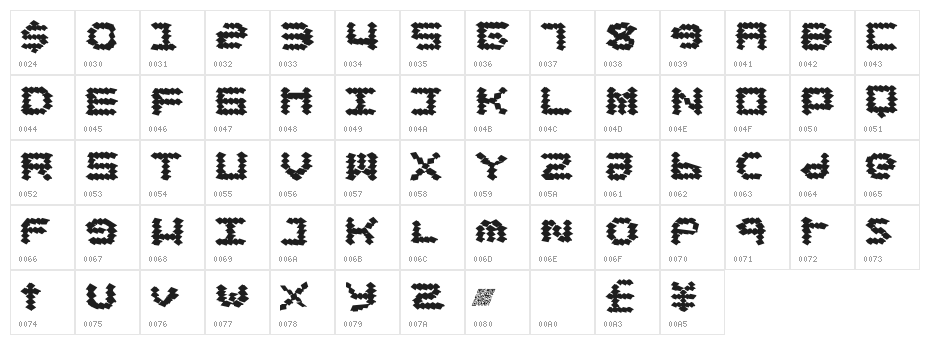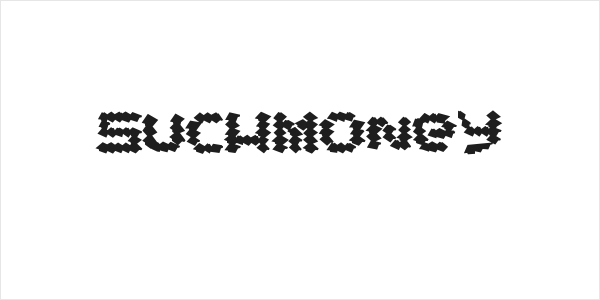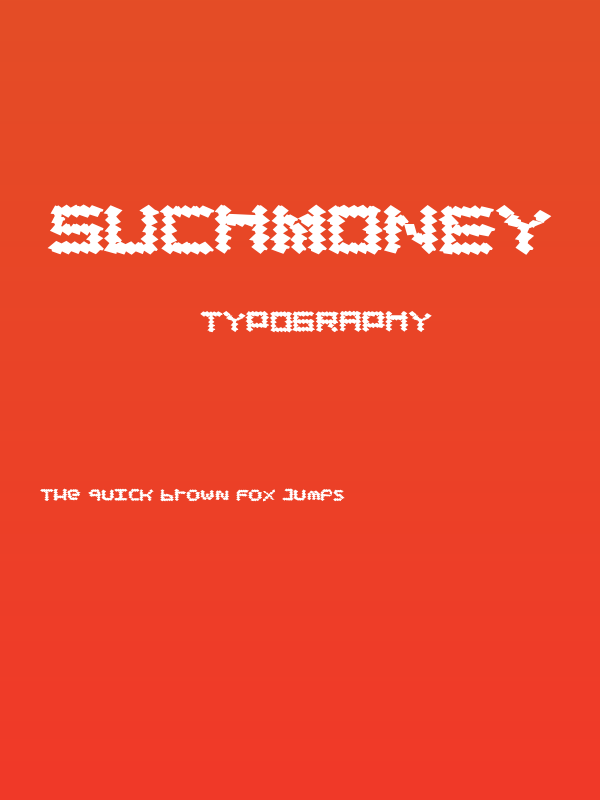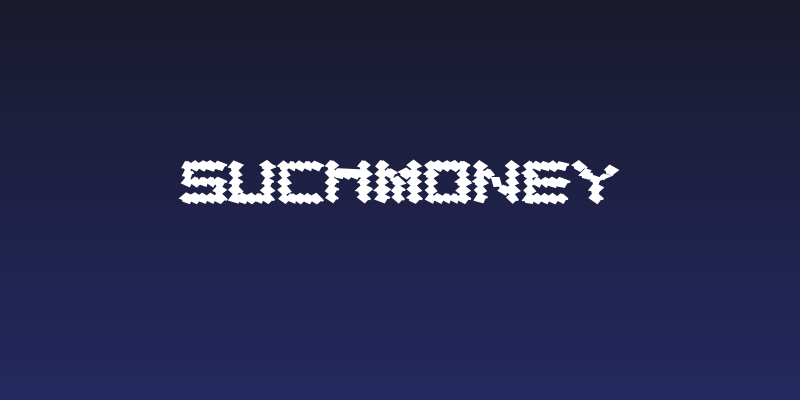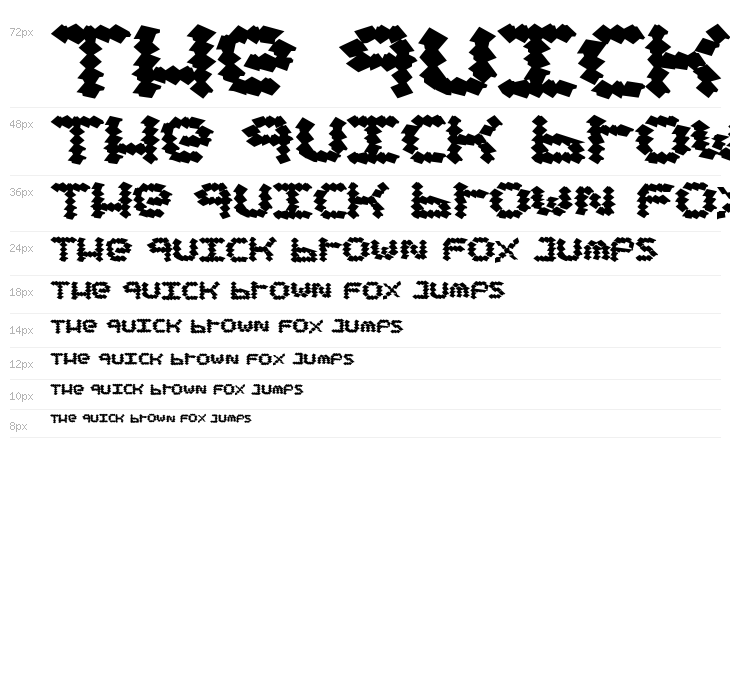
SuchMoney Font
| Progetti proposti | Ideal for branding projects, album covers, posters, and any design work that requires a bold and modern statement. |